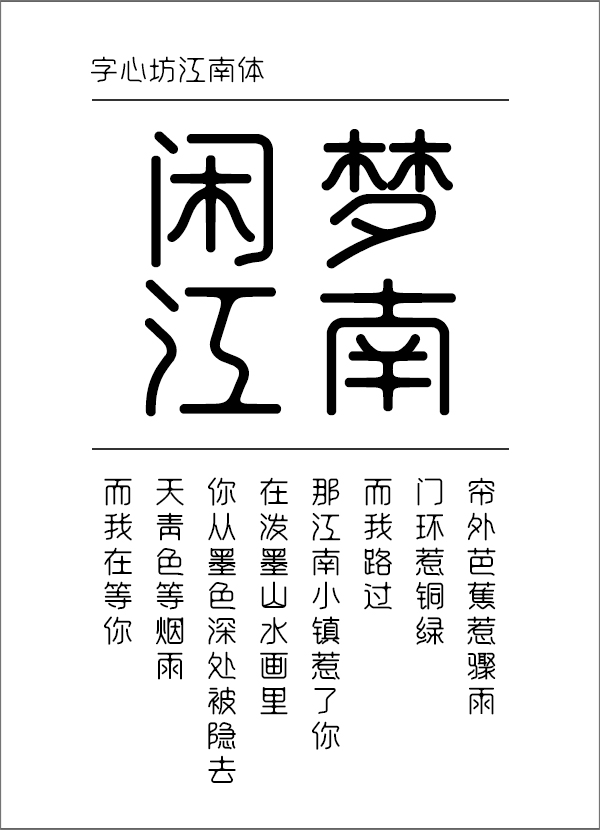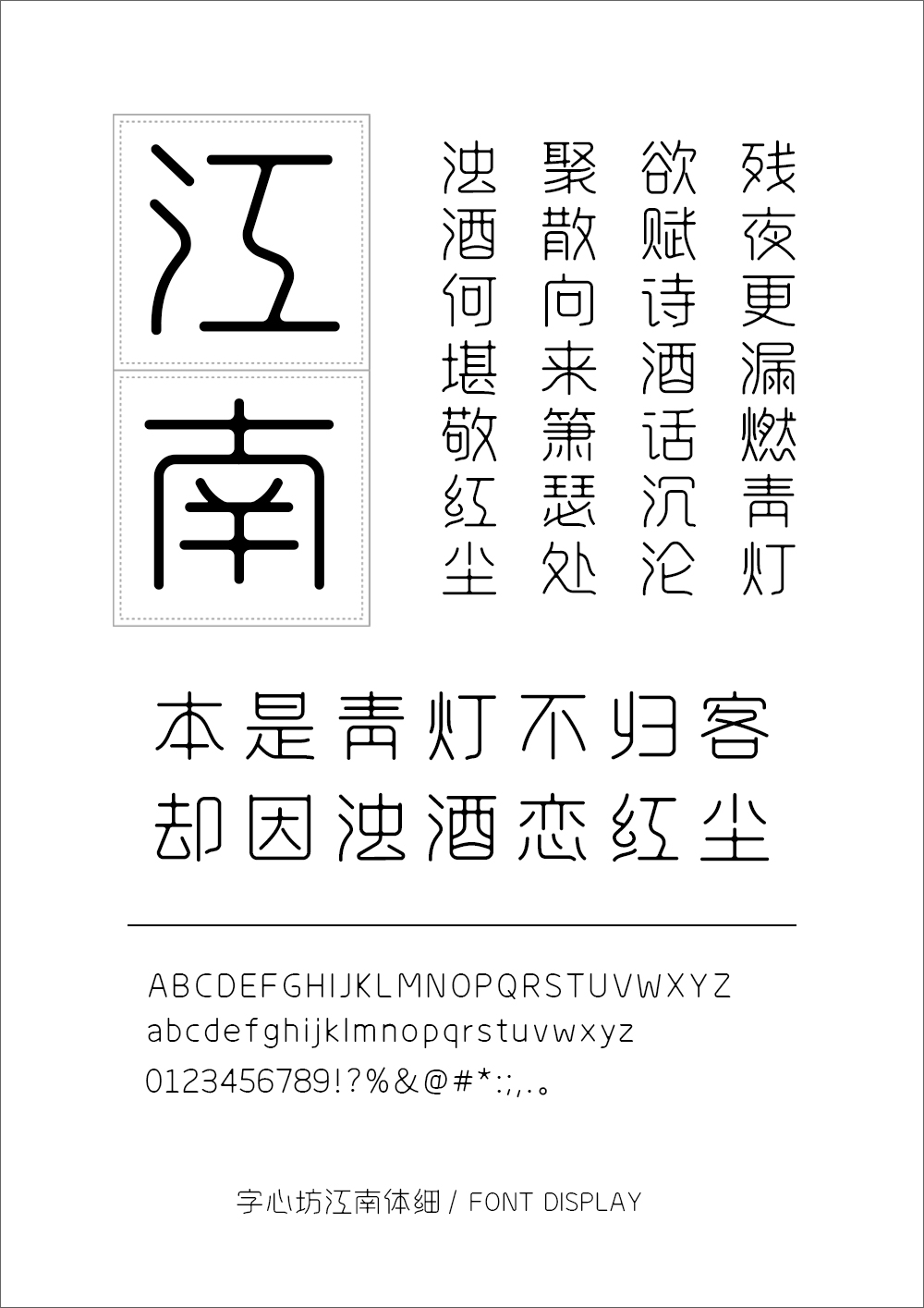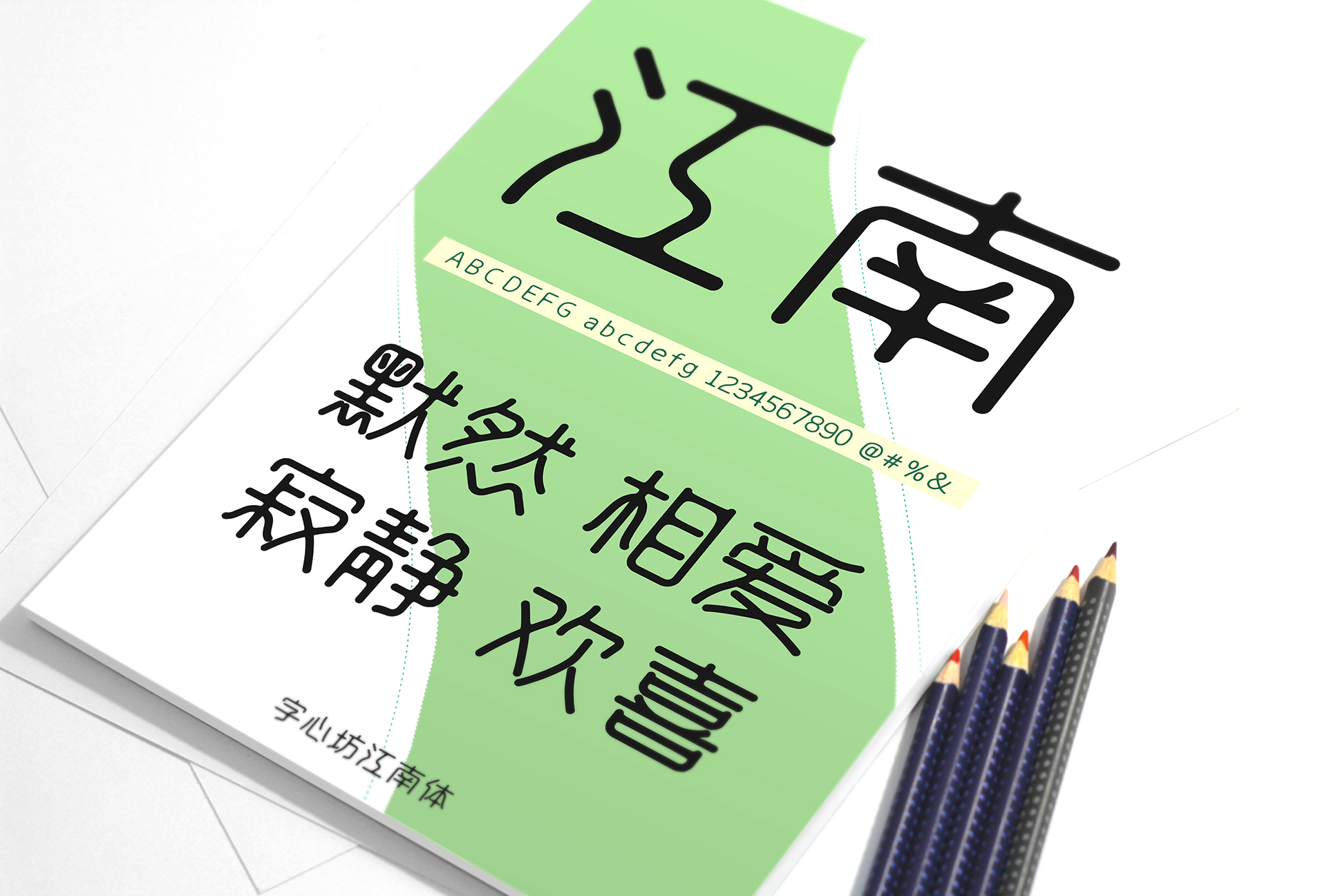
字心坊江南体
字体采用非衬线设计,字形融合中国小篆与黑体字的特点,取小篆的设计元素,同时力求精简,简化篆书,古为今用,在保证最大化识别度的基础上,在变化中求得篆书之韵,尽显古风之美。此款笔画采用柔线柔边设计,自然流畅,在曲径回廊般的柔线中,仿佛置身于如诗如画的烟雨江南。
字体风格:简约 / 古风 / 时尚 /无衬线
推荐场景: 标志 / 导视 / 书籍 / 游戏 / 动漫 / 影视 / 屏显